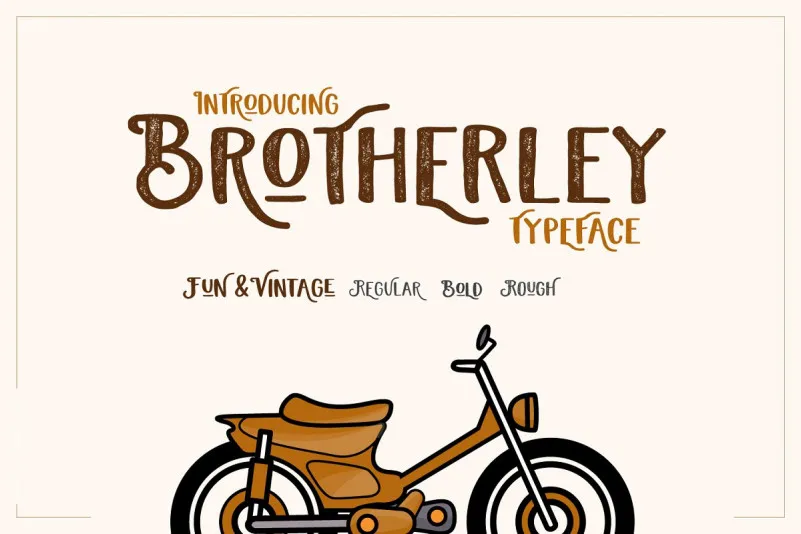
Brotherley Typeface – Download Grátis
A fonte Brotherley Typeface é uma escolha perfeita para os designers que procuram um estilo vintage com um toque divertido e original. Inspirada nos antigos modelos de motocicleta, essa fonte sans-serif apresenta um caráter malicioso e desafiador, como se as letras fossem desenhadas por alguém com uma mão esperta e criativa. Através do uso da Brotherley Typeface em t-Shirts infantis ou adultas, posteres, logomarcas e muito mais, você pode transmitir um charme vintage enquanto mantém o seu design atualizado e divertido. Brotherley Typeface é uma fonte de estilo moderno que combina elementos antiquados com design cuidadosamente elaborado. As três variantes básicas – regular, bold e uma aparência grossa – permitem que os designers criem designs que se adequam perfeitamente às suas necessidades. Além disso, o uso de estilos específicos em algumas letras permite que as personalizações sejam ajustadas dentro dos seus projetos. Esta fonte não só é um ótimo complemento para as fontes vintage tradicionais, como também é perfeita para aplicações variadas, incluindo t-shirts infantis e adultas, posteres, logomarcas e muito mais.